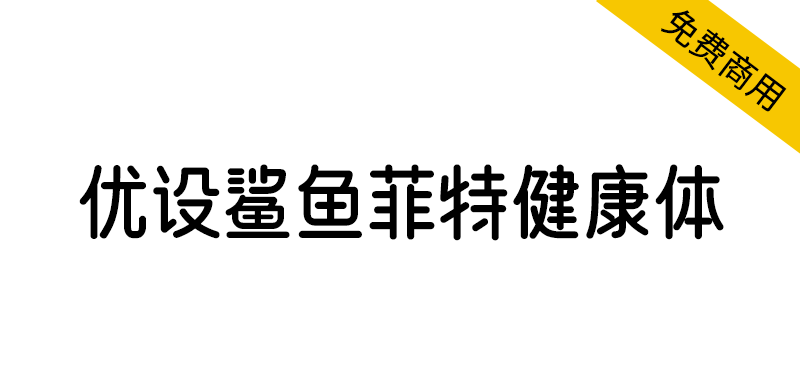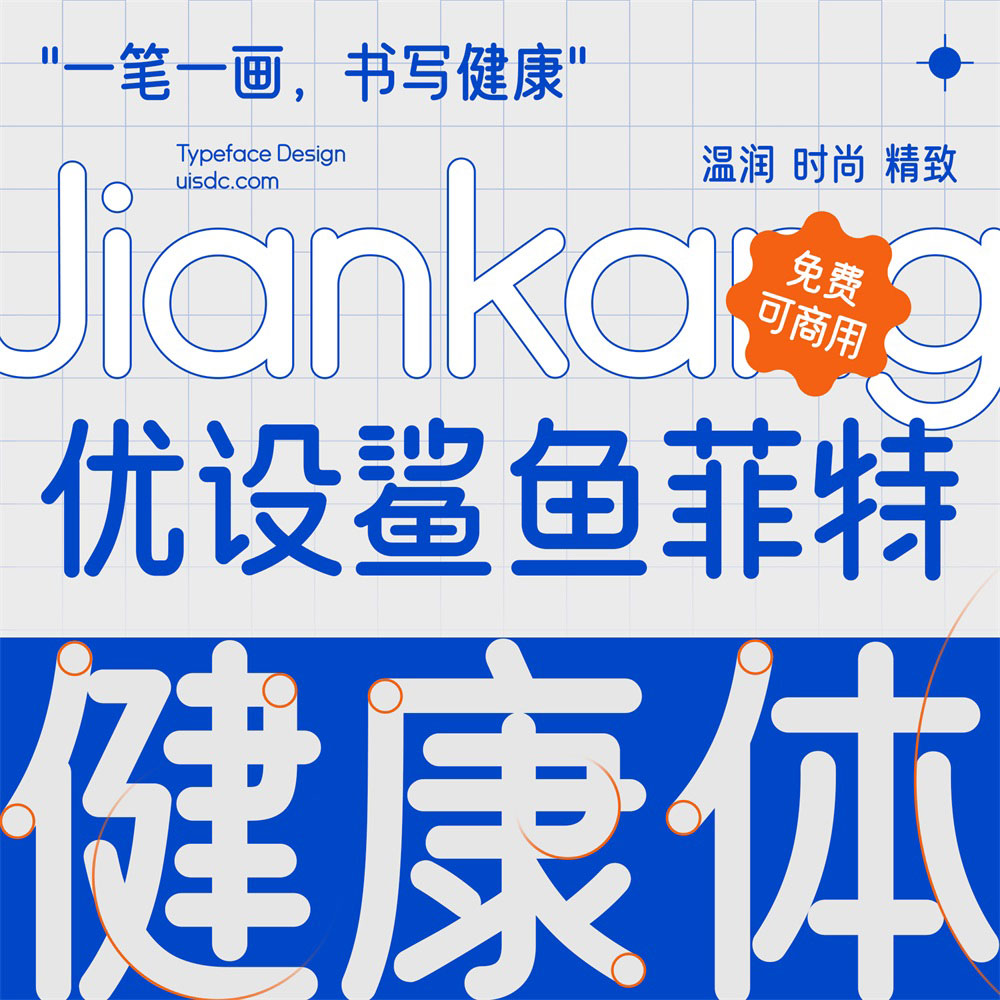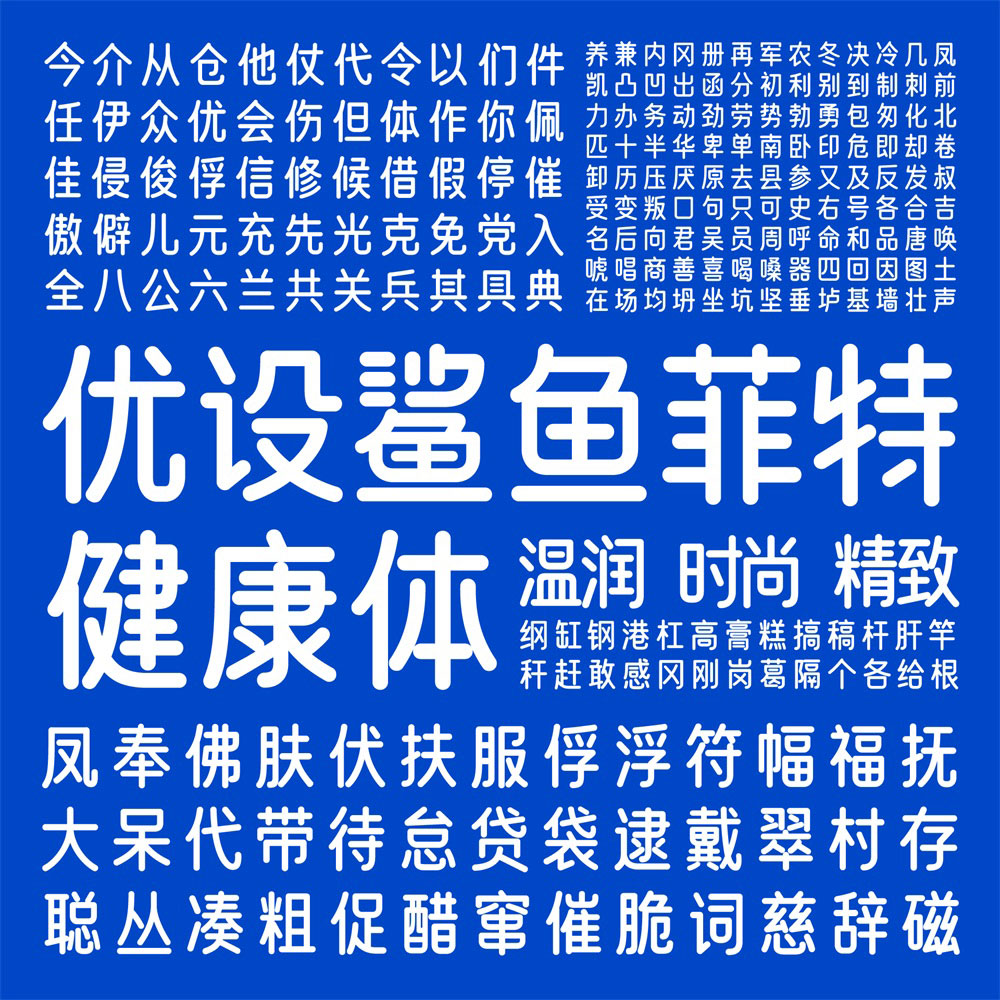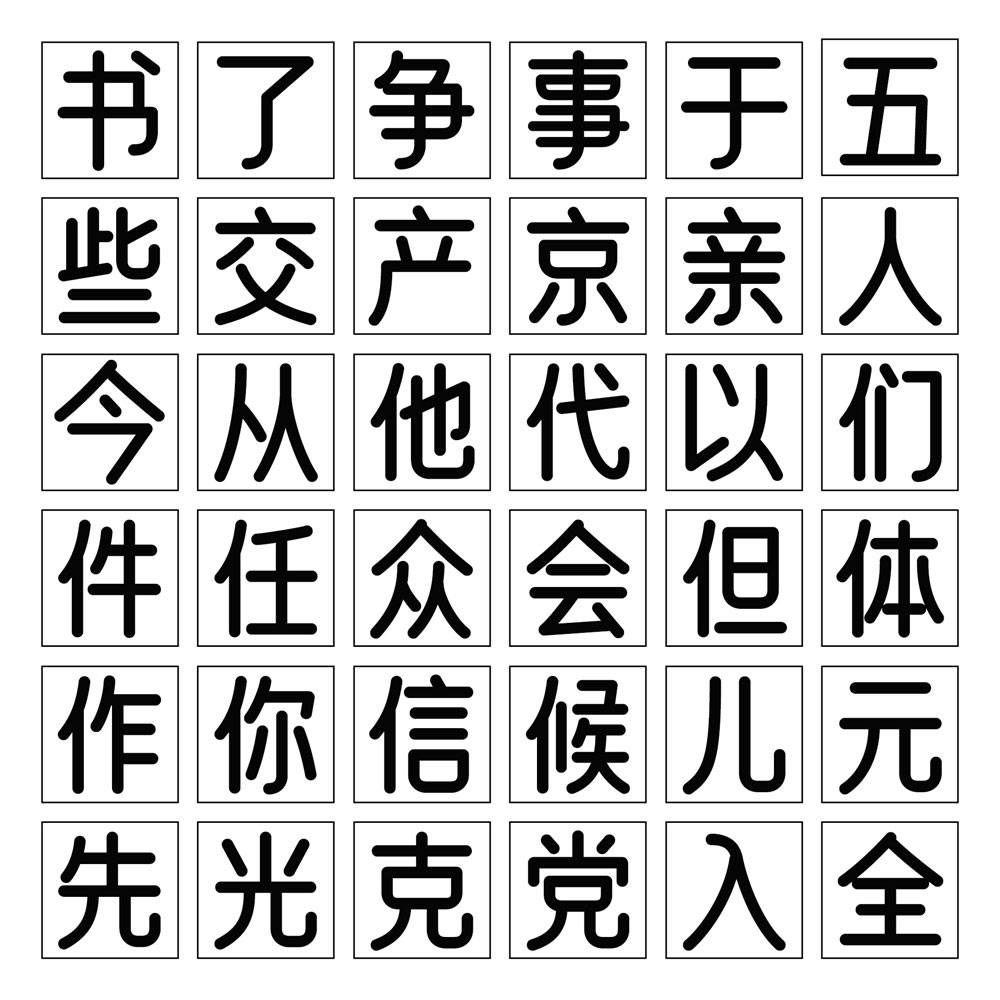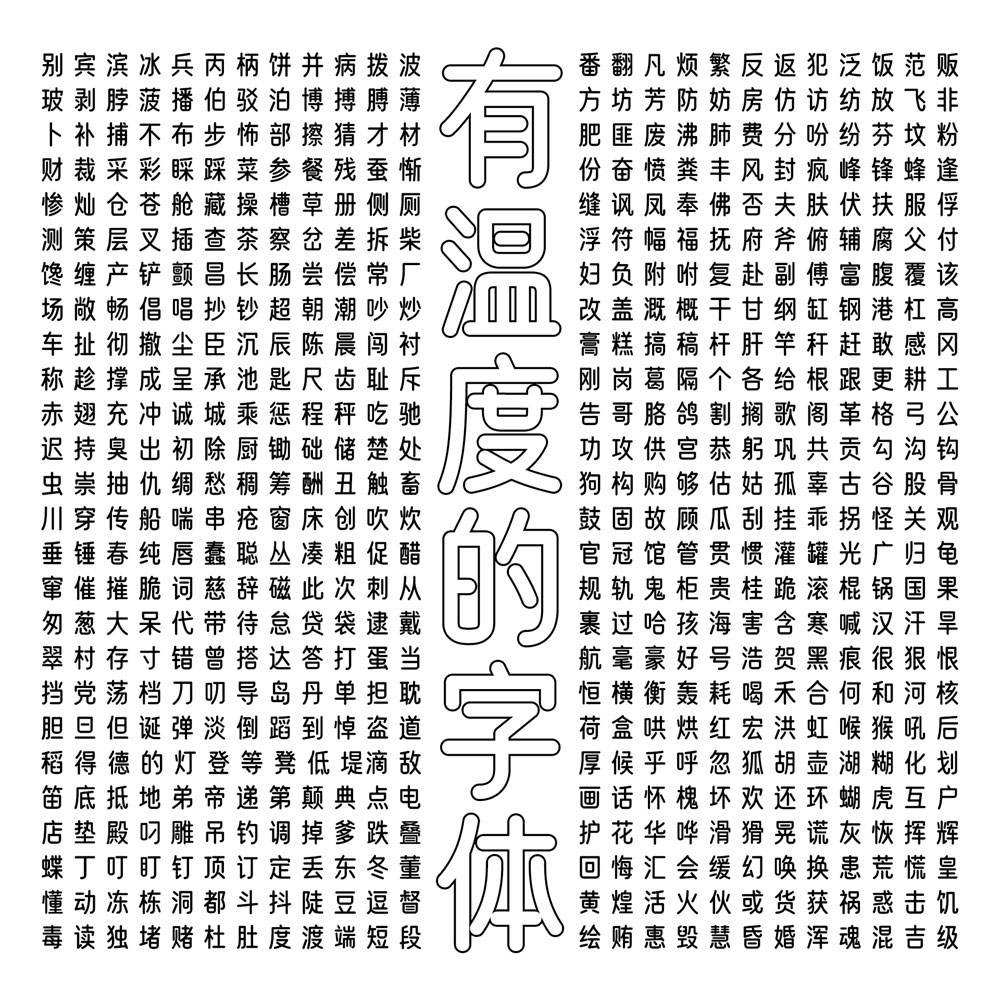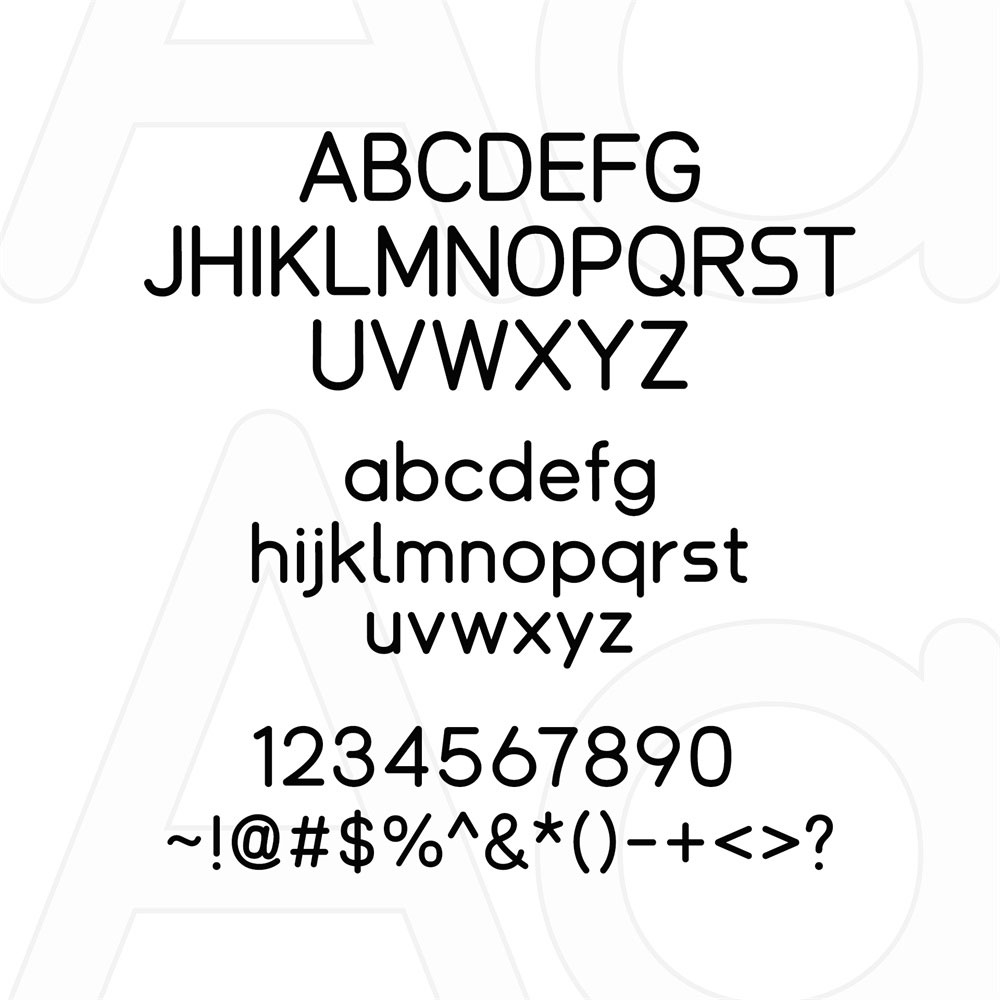
【优设鲨鱼菲特健康体】一款电商应用场景极强的优质字体
优设鲨鱼菲特健康体是由字绘中国发起,新零售健康轻食品牌鲨鱼菲特联合优设与字由,为广大设计师特推出了一款专为健康而生,电商应用场景极强的优质字体。
优设鲨鱼菲特健康体是优设好身体的升级版,造型上要比优设好身体更具有辨识度,设计上更加贴近健康品牌附有的亲和力和现代感,不仅会成为电商设计的又一大助力,更体现了当下追求健康的年轻用户群体特性。
字体设计之初是作为健康轻食品牌“鲨鱼菲特”的品牌 logo 去创作设计的。在符合当下追求健康的年轻用户群体调性的同时保持了品牌亲和力。
现整套字体在原有圆体圆润的外观和优美的弧度下,对字形、笔画细节进行再设计,结构纵向拉长,体现健康体态的纤细匀称感;同时在一些笔划转角、弧度控制曲线让细节之处富有一些硬挺的视觉感受。使字体整体风格更轻快时尚又不失精致与稳重感。